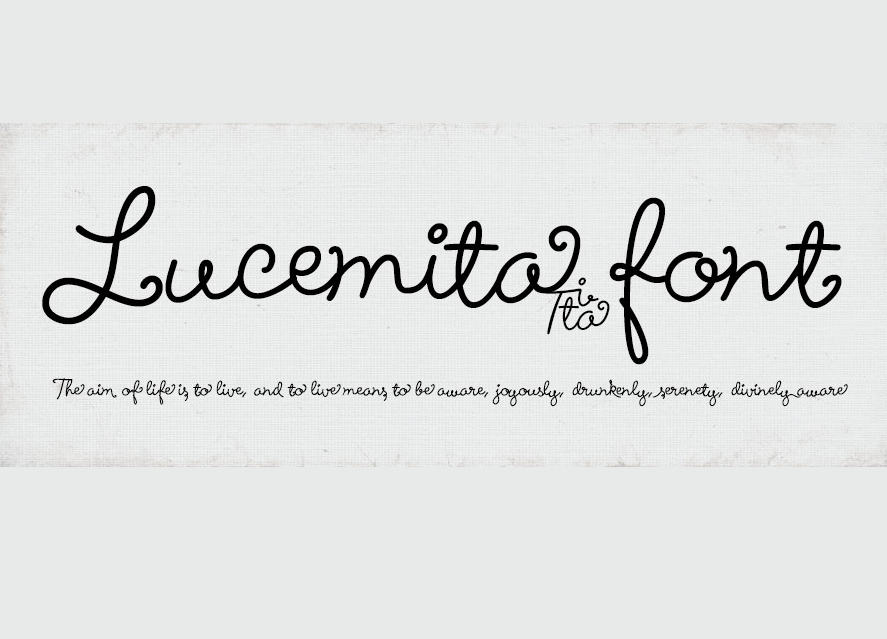
Lucemita Font
A Lucemita Font é uma fonte autenticamente escrita, cuidadosamente criada pelo designer Hamilton. Esta fonte oferece um toque único e original para qualquer projeto que você esteja lidando com – seja um trabalho de escritório ou arte gráfica. No design da Lucemita, o designer Hamilton incorporou dois conjuntos completos de letras maiúsculas, permitindo inúmeras opções para títulos. Além disso, há uma única letra minúscula que pode ser usada como “swashes” (pontilhagens), uma característica Open Type que permite criar e personalizar estilos de escrita únicos. Se você está procurando por algo diferenciado para seus projetos digitais, a Lucemita Font é uma ótima opção. Para ver todas as funções do tipo personalizado, basta baixar o nosso PDF anexado. Esta fonte autografada e de qualidade oferece um toque único em qualquer projeto que você esteja desenvolvendo.